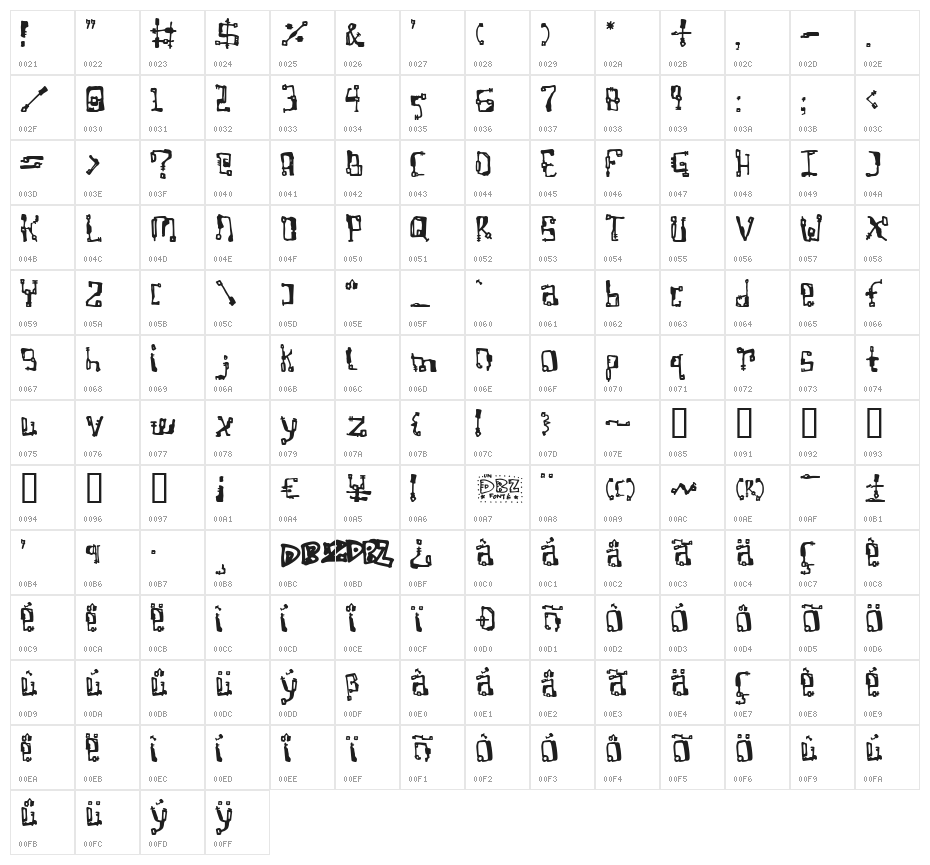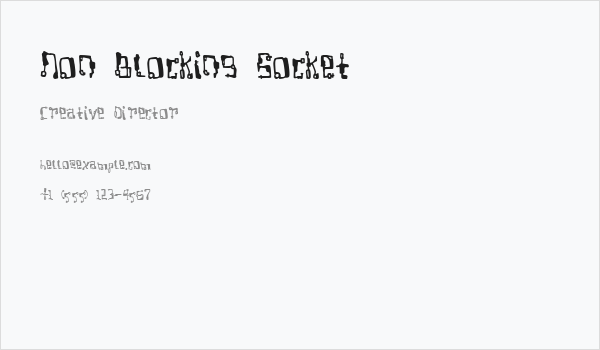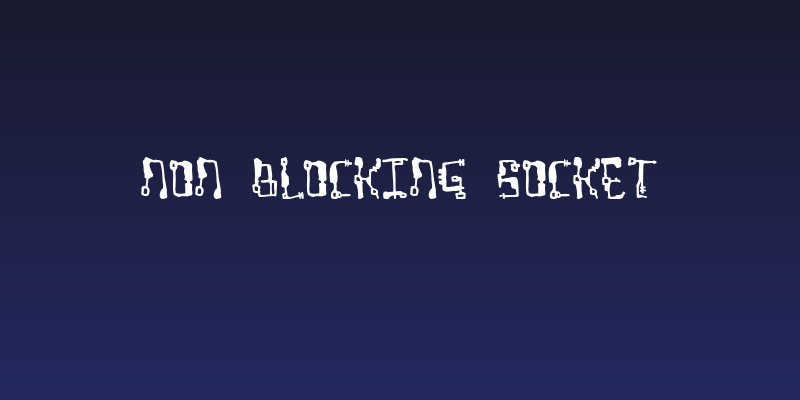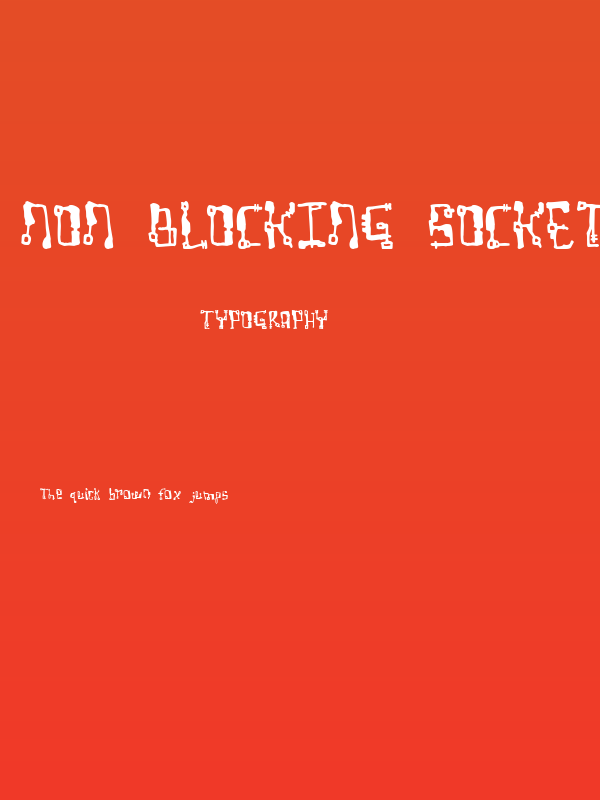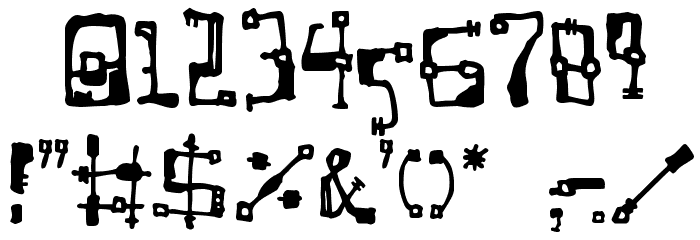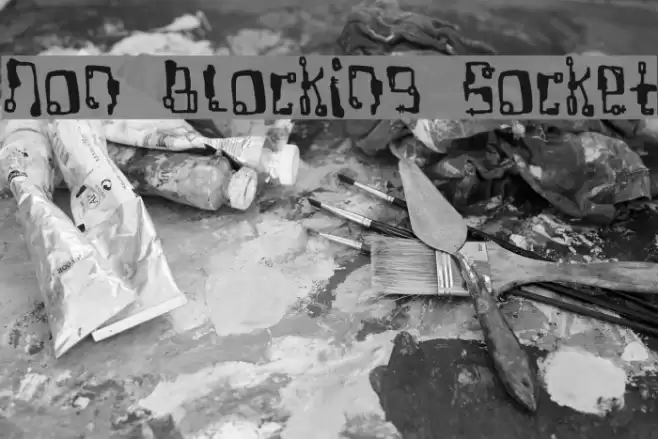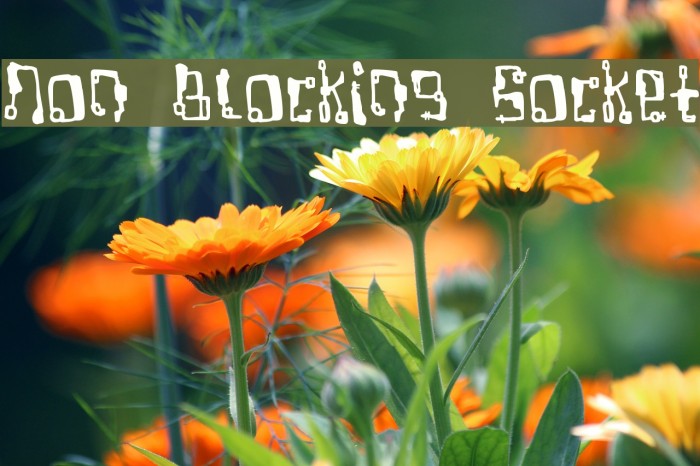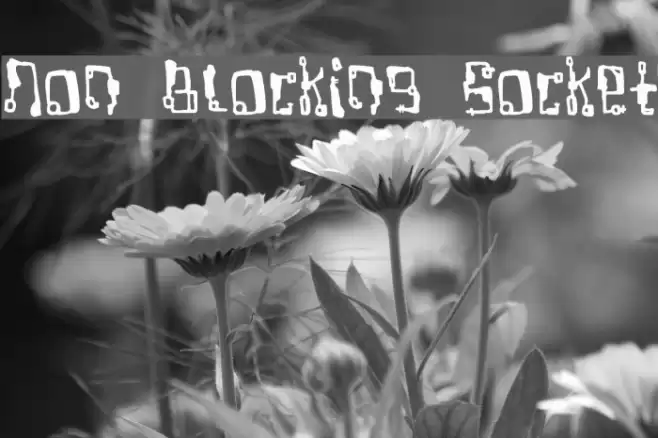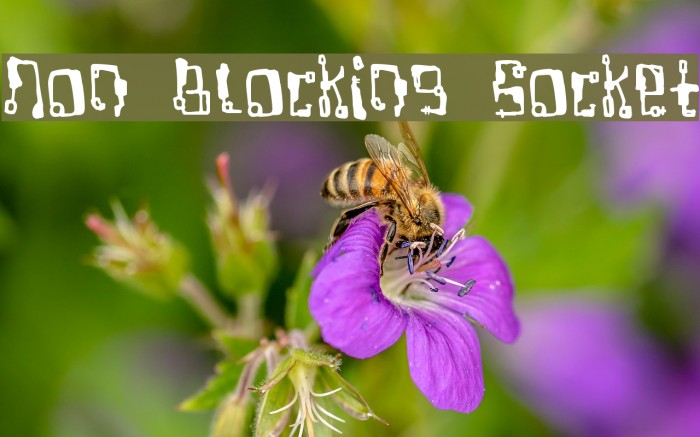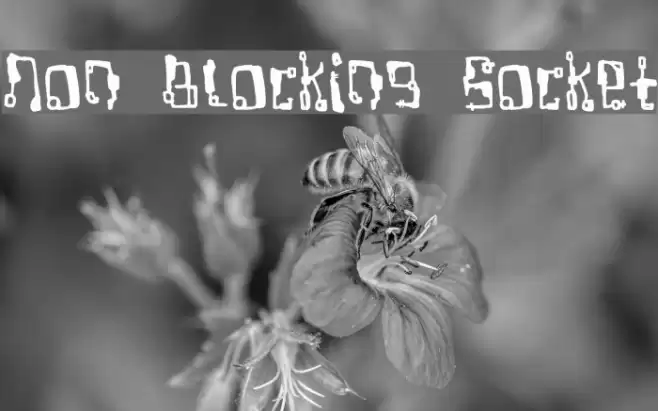
Non Blocking Socket Font
| 名前 | Non Blocking Socket |
| 用途 | Logos, Posters, Artistic Projects |
| おすすめプロジェクト | Ideal for projects that require a unique and artistic touch, such as posters, album covers, or branding for tech or industrial-themed events. |